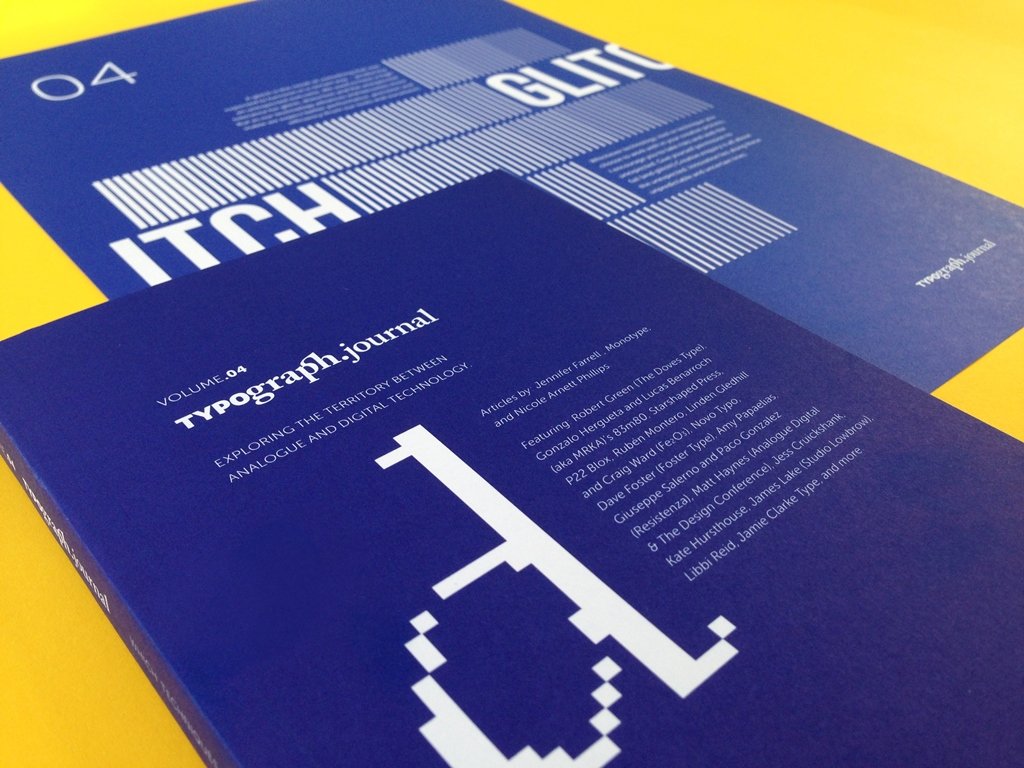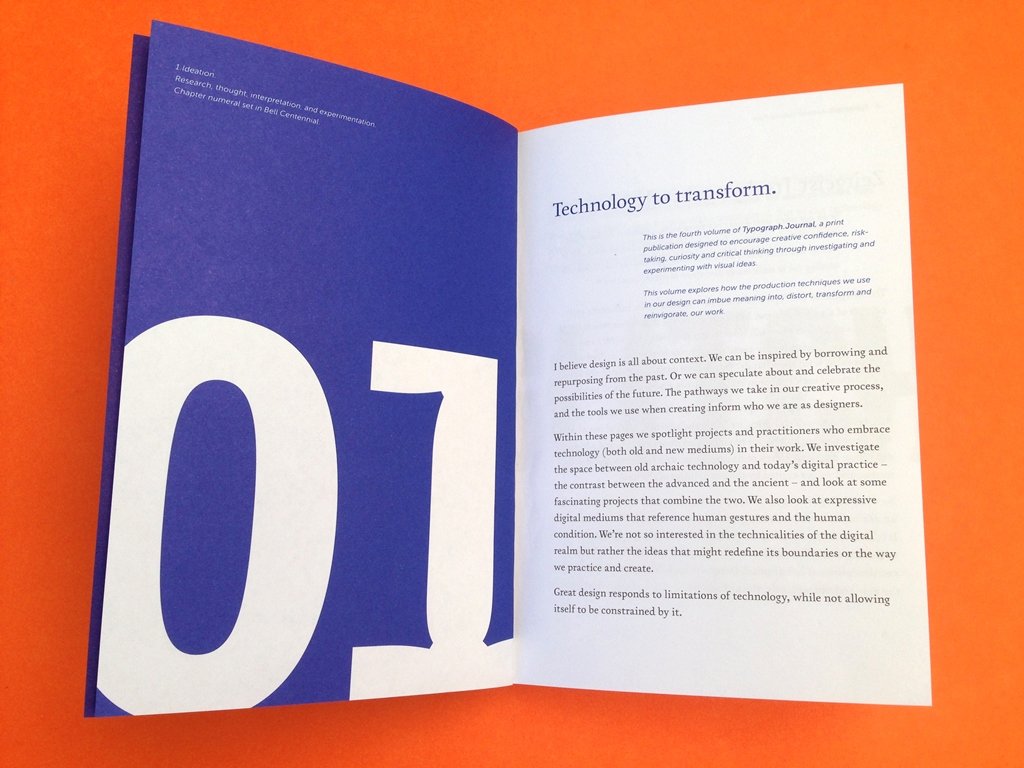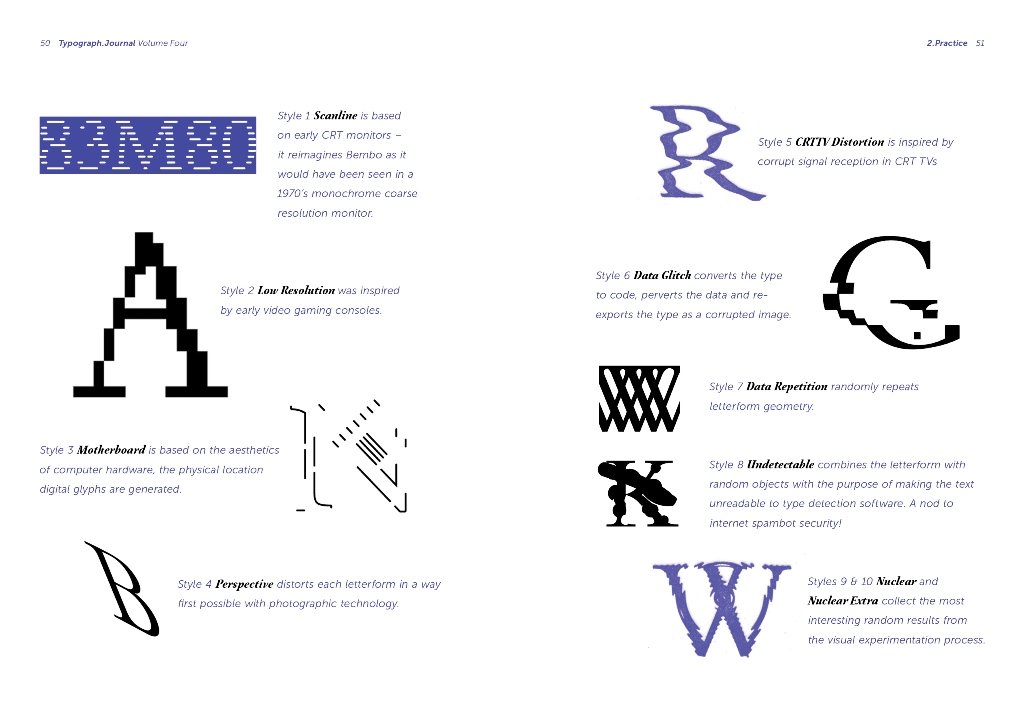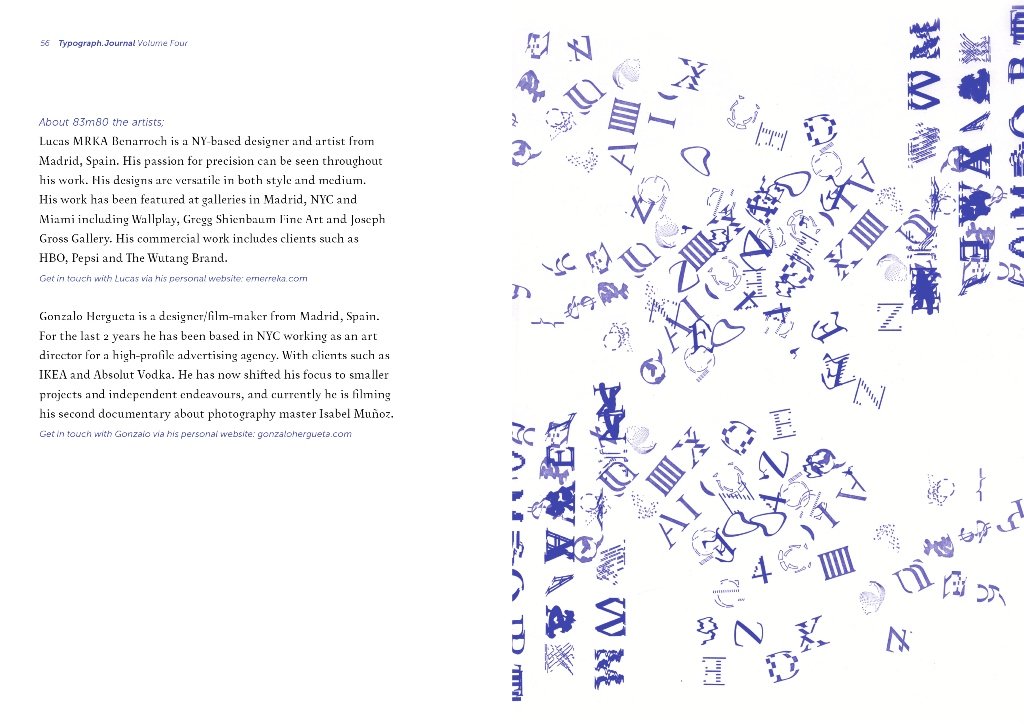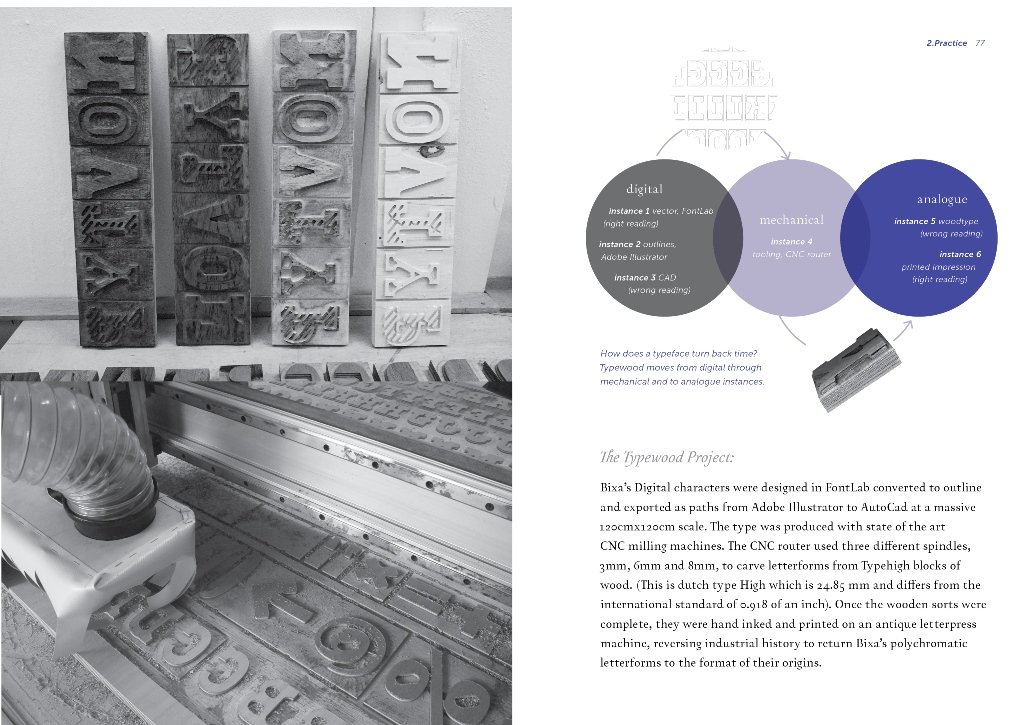
Typograph.Journal, vol. 04, Nicole Arnett Phillips, 2016.
Typograph.Journal, un homenaje a la tipografía de Nicole Arnett Phillips
La revista Typograph.Journal es todo un homenaje al mundo de la tipografía, de la caligrafía y del lettering. Nacida de la creatividad de la tipógrafa australiana Nicole Arnett Phillips, la publicación ofrece un espacio de propuestas, ideas e inspiraciones a disposición de los lectores y su cuidada selección de textos, entrevistas e investigaciones visuales pide una lectura activa, en la que las ideas de los demás se conviertan en un impulso para la creación y el desarrollo de nuevas ideas. A día de hoy, Typograph.Journal cuenta con cuatro números, todos ellos construidos alrededor de una pregunta. Si los primeros tres volúmenes se preguntaban si un texto puede ser a la vez legible y experimental, dónde reside y se alimenta la creatividad y cómo unir matemáticas y belleza, el cuarto —distribuido en abril de 2016— se pregunta cuáles técnicas y tecnologías están remodelando el diseño contemporáneo. Un grupo de estudios y creativos, formado, entre otros, por The Doves Type, Gonzalo Hergueta y Lucas Benarroch, Starshaped Press, Craig Ward, Novo Typo, Dave Foster, Amy Papaelias, Resistenza, Matt Haynes y Jamie Clarke– reflexionan acerca de la relación entre técnicas tradicionales y tecnologías a la vanguardia, métodos artesanales y medios digitales; en cómo actualmente coexisten y se enriquecen mutuamente.
Typograph.Journal, vol. 04, Nicole Arnett Phillips, 2016.
Typograph.Journal, Nicole Arnett Phillips, 2014-2016.
Typograph.Journal, vol. 04, Nicole Arnett Phillips, 2016.